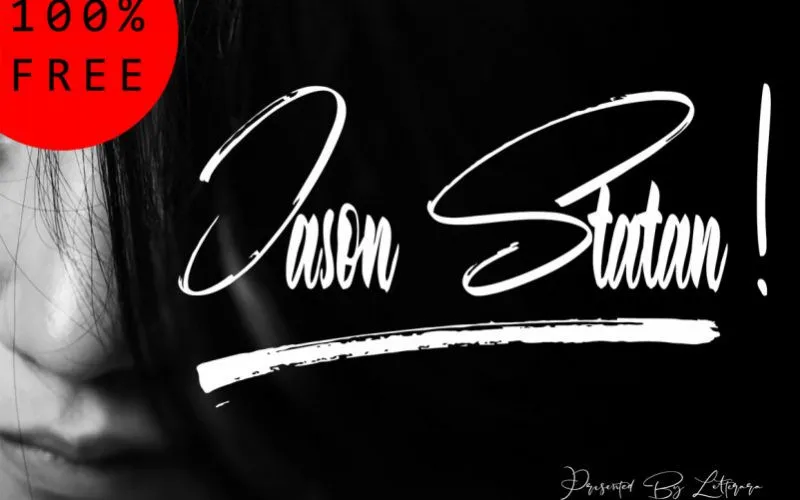
Jason Statan Handbrush Font – Fonte Grátis
Jason Statan Handbrush Font
Esta é uma fonte script com estilo de desenho à mão, criada para imitar a sensação de esfregar um pincel no papel sem preenchimento. O design destaca elementos naturais e suaves, como pequenos buracos na superfície que dão ao resultado um aspecto quase desbotado. Ideal para aqueles que buscam uma fonte específica para logotipos, roupas, convites, marcações, embalagens e anúncios. Introduzimos a Jason Statan Brush Font de Thomas Aradea para quem procura um design minimalista, porém sofisticado. A família de caracteres está disponível em várias versões, cada uma adaptada à sua função específica. Glarious é uma fonte brush que se destaca pela sua simplicidade e elegância. Esta fonte foi projetada com cuidado para atender a necessidades específicas do design gráfico e impressão. Ela oferece um padrão de escrita limpo e consistente, mas também permite diferentes modos de usinagem para criar uma identidade visual única que se destaca em qualquer situação. É perfeita tanto para aplicar na web quanto para impressão final, proporcionando texturas e sutilezas únicas à sua obra. Com o Jason Statan Brush Font de 24Design, você pode explorar a versatilidade desta fonte no design gráfico digital e em impressão. Seja para criar seu próximo projeto editorial ou desenvolver uma marca inovadora, esta fonte está equipada para suportar suas necessidades criativas.